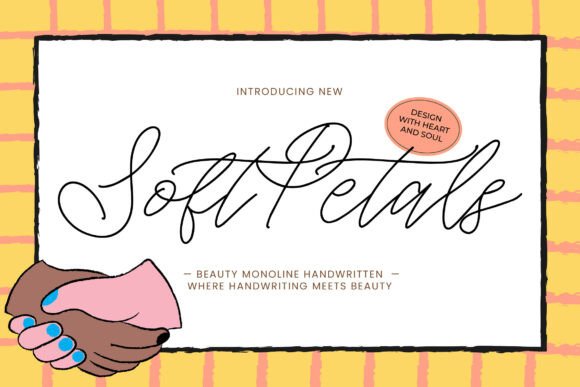
Soft Petals
Une Politesse Élégante et Naturelle avec Soft Petals
Soft Petals est bien plus qu'une police de caractères : il s'agit d'une véritable œuvre d'art typographique qui apporte une touche de douceur et d'intimité à toute création. Conçue en ligne fine et fluide, cette police écriture manuscrite capte l'essence de la grâce naturelle, idéale pour les marques qui souhaitent exalter la beauté organique et le côté humain de leurs projets.
Que vous souhaitiez créer des étiquettes de cosmétiques naturels, des invitations de mariage minimalistes ou des publications sociales inspirantes, Soft Petals s'adapte à tous les supports avec une élégance discrète mais puissante.
Pourquoi Choisir Soft Petals ?
- Taille fine et fluidité : Des traits légers et des boucles aériennes qui rappellent l'écriture à la main, parfaits pour un look délicat et personnel.
- Polyvalence : Idéal pour le sector de la beauté, le mariage, ou les contenus créatifs en ligne.
- Impact émotionnel : Une typographie qui évoque la chaleur humaine, parfaite pour capter l'attention sans agressivité visuelle.
En résumé, Soft Petals est une invitation à glisser une pointe de poésie dans chaque projet. Qu'il s'agisse de vectoriser un logo, d'écrire un message personnalisé ou de sublimer un emballage, cette police est un outil incontournable pour les amateurs de design subtil et raffiné.